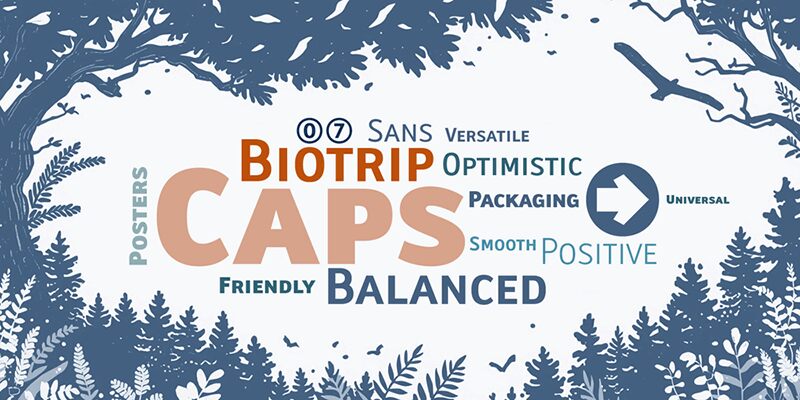
Biotrip Caps Bold de deFharo es una tipografía sans serif gratuita en mayúsculas, con un estilo rotundo y futurista. Sus letras son pesadas y compactas, construidas a partir de trazos anchos, esquinas suaves y grandes formas circulares, lo que le aporta un aire de ciencia ficción amable, evitando esa frialdad puramente geométrica.
Encaja perfectamente en pósteres, branding de videojuegos, portadas de álbumes, gráficos para eventos tecnológicos y títulos cortos donde se busca una estética retro-futurista. Al ser una fuente gratuita, también es una opción ideal para titulares, logotipos y monogramas, ya que sus mayúsculas redondeadas y sólidas funcionan mejor cuando el texto es breve.
Biotrip Sans Caps is a multipurpose typeface, refined down to the last detail. It includes seven weightsLight, Regular, Medium, Semi Bold, Bold, Extra Bold, and Blackthat allow for the creation of solid, adaptable, and expressive visual systems.
Each variant has been carefully designed to preserve the humanist essence of Biotrip Sans, with the authority of capital letters.